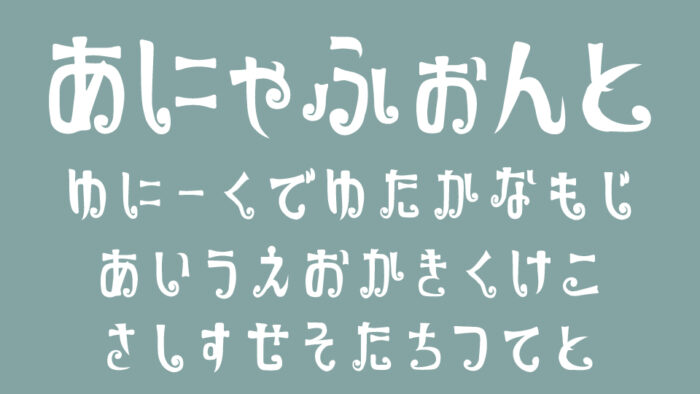
あにゃふぉんと
あにゃふぉんとは、アニメ「SPY×FAMILY」のOPのテロップにインスパイヤを受け制作されたデザインフォントです。
文字の端にくるんとカールした装飾がついた、遊び心あふれる「SPY×FAMILY」OPテロップの世界観がうまく表現されているフォントです。すべての文字にどこか気の抜けた可愛さがあり、アーニャのような可愛さです。
収録文字は、ひらがな・アルファベット・記号が収録されています。